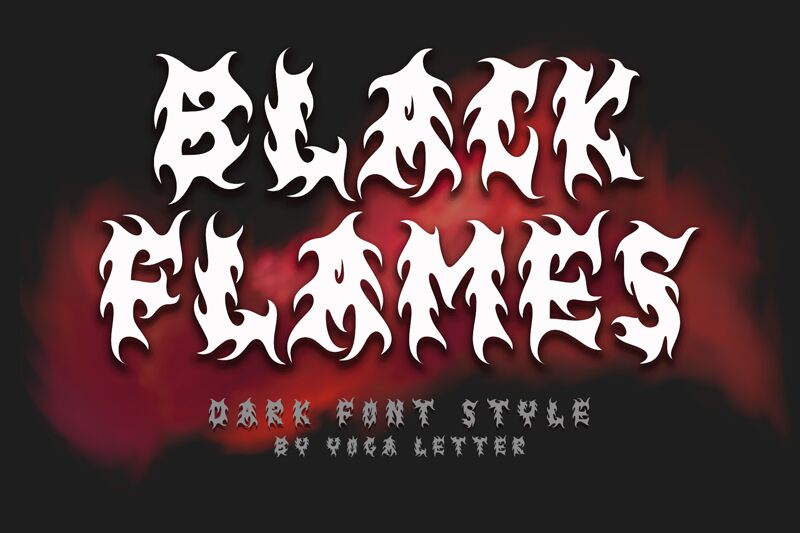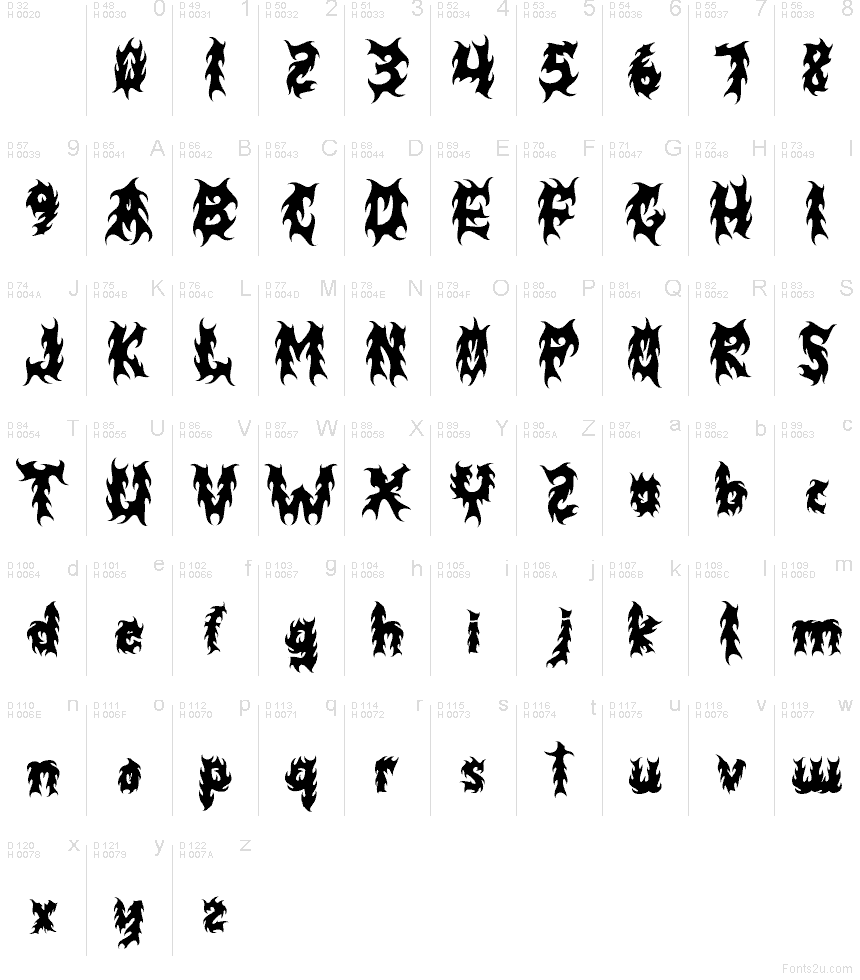
BLACK FLAMES
Black Flames de Yoga Letter es una tipografía display gótica gratuita con trazos que evocan llamas, puntas curvadas y aberturas profundas que otorgan a cada letra un aspecto tallado y deformado por el calor. Las formas mantienen un carácter afilado e irregular, creando un ritmo decorativo oscuro sin necesidad de ornamentos adicionales.
Black Flames funciona a la perfección en pósteres de terror, portadas de álbumes de metal, diseños para tatuajes, flyers, logotipos y gráficos de videojuegos donde se requiere una estética potente y temática. Esta fuente gratuita también es ideal para titulares, portadas y ropa personalizada, ya que sus formas dentadas tienen suficiente fuerza para sostener el diseño por sí solas.